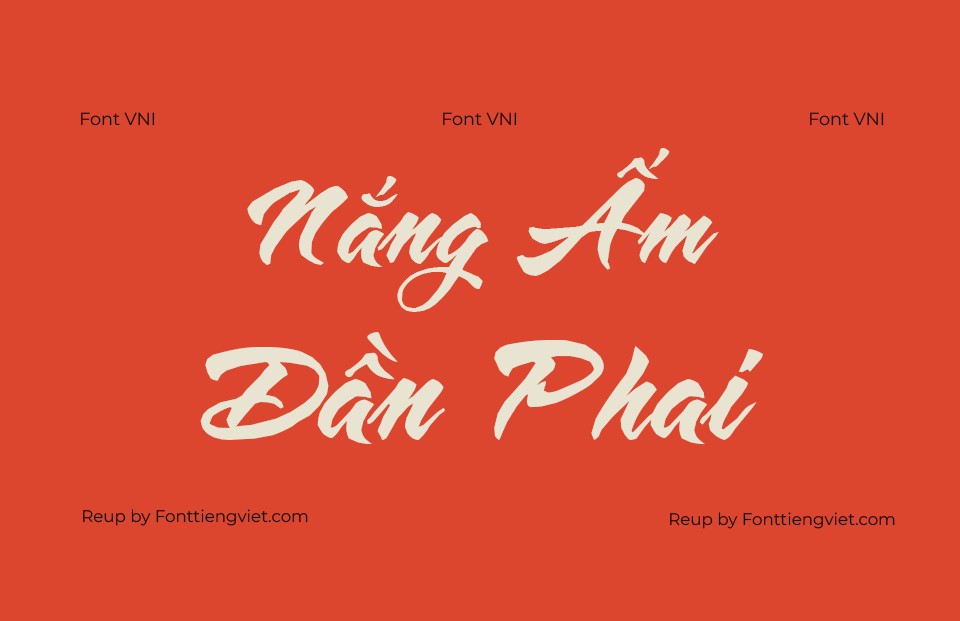
Font Việt hoá VNI Butlong
Font Việt hoá VNI Butlong – Lựa chọn hoàn hảo cho nét chữ thư pháp hiện đại
Giới thiệu về Font Việt hoá VNI Butlong trong thiết kế
Trong thế giới đồ họa, việc tìm kiếm một bộ Font Miễn Phí có khả năng truyền tải sự mềm mại và uyển chuyển là điều rất quan trọng. Font Việt hoá VNI Butlong nổi lên như một giải pháp lý tưởng dành cho những ai yêu thích phong cách chữ viết tay bằng bút lông truyền thống. Đây là bộ font được tối ưu hóa để phù hợp với bảng mã VNI phổ biến, giúp người dùng dễ dàng thể hiện các nội dung tiếng Việt có dấu một cách trơn tru và thẩm mỹ nhất. Với những đường nét thanh đậm tự nhiên, bộ chữ này tạo nên cảm giác gần gũi, chân thực cho mọi bản thiết kế.
Tại sao nên sử dụng Font Việt hoá VNI Butlong?
Đặc điểm nổi bật nhất của Font Việt hoá VNI Butlong chính là sự mô phỏng chính xác kỹ thuật đi bút của các thư pháp gia. Các nét chữ không quá cứng nhắc mà có độ bay bổng, rất phù hợp cho các bài thuyết trình tại trường học, thiết kế thiệp mời hoặc làm báo tường. Việc sử dụng font chữ này giúp các em học sinh và thầy cô giáo tạo ra những sản phẩm học tập sinh động, mang đậm dấu ấn cá nhân và nét văn hóa Việt Nam đặc trưng.
Cách ứng dụng Font Việt hoá VNI Butlong hiệu quả
Để phát huy tối đa vẻ đẹp của bộ font này, bạn nên kết hợp với các tông màu trầm hoặc màu mực tàu trên nền giấy giả cổ. Font Việt hoá VNI Butlong thường được ưu tiên dùng cho các tiêu đề lớn, câu đối hoặc những đoạn văn ngắn cần sự nhấn mạnh về cảm xúc. Lưu ý nhỏ khi sử dụng là bạn cần chuyển đổi bảng mã trên Unikey sang VNI Windows để tránh lỗi hiển thị ký tự. Sự linh hoạt của font giúp nó xuất hiện phổ biến từ các bìa sách giáo khoa đến các poster sự kiện văn hóa nghệ thuật.